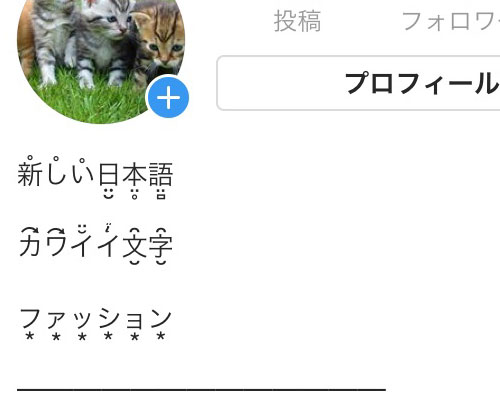
インスタのフォントで日本語をオシャレにする方法!プロフィールの日本語を変えてみよう
インスタのプロフィールには自己紹介を書く場所があって個性的なプロフィールにしている方もいますよね。
ちょっとした工夫でオシャレなプロフィールを作る事もできます。
例えば、英語(アルファベット)の場合は太字や斜体などのフォントを変える事もできます。
インスタのフォントで日本語をオシャレにする方法!プロフィールの日本語を変えてみよう
フォントが変わると印象もかなり変わりますよね。
こういうフォントで日本語の変更もできるのか気になる方も多いのではないでしょうか。
そこでこのページでは日本語のフォントについて調査してみました。
インスタのフォントで日本語をオシャレにする方法
インスタのフォントで日本語をオシャレにする方法!プロフィールの日本語を変えてみよう
まず先に結論からお伝えすると、日本語のフォント自体を変更する事はできませんでした。
しかし、日本語のフォントと記号などを加工したり組み合わせる事で日本語自体の見た目を変える事ができます。
日本語の見た目を変える方法としては以下の3つがあります。
• へた字を使う
• ギャル文字を使う
• 日本語で特殊文字を作る
それぞれの方法について以下で詳しく解説します。
へた字を使う
へた字と呼ばれる文字を使えば少し手書きっぽい日本語を使う事ができます。
例えば以下のような文字です。
कƖ ı੭ੇʑ̸̀Ⴛ̅̀
ᓓ̸₹ㄑ⇂ȷ̶ ૅੁ
ㄜιནㄝƺ
このような文字をへた字と言われています。
通常の文字よりも崩した文字で、へたな文字という感じですね。
へた字はスタイリッシュな感じではありませんが、ちょっと印象に残したいような言葉をあえてへた字にしておくと良いかもしれません。
ギャル文字を使う
ギャル文字とはガラケー時代のギャルと呼ばれる女子高生がよく利用していた文字です。
記号を組み合わせて日本語のひらがなを表現しています。
例えば、以下のような文字がギャル文字と呼ばれてます。
ぁしヽぅぇょゝ
ヵゝ(≠<しナ⊇
±U£世ξ
ギャル文字で長い文章を書かれるとパッと見は読めない状態になります。
しかし、ギャル文字に慣れてくるとちゃんと読めるようになるので面白いですね。
当時のギャルが愛用していた文字という事もあって、ギャル文字を使うとへた字よりも可愛い感じに仕上がります。
日本語で特殊文字を作る
上記で紹介したへた字とギャル文字は日本語の『ひらがな』を変える事ができましたが、漢字を変えたいというケースもありますよね。
そういう時に使えるのが特殊文字を作る方法です。
日本語で特殊文字を作ると以下のように漢字やカタカナなども可愛い感じで作る事ができます。
新̊し̊い̊日̤̮本̤̥語̤̻
カ⃕ワ⃕イ̆̈イꙶ文̮̑字̮̑
フ͙ァ͙ッ͙シ͙ョ͙ン͙
ひらがなだけならへた字やギャル文字が使えますが、漢字やカタカナを変えたい時には日本語の特殊文字を作るのが一番でしょう。
まとめ
インスタで日本語のフォントを変えるにはここで解説したように特殊文字を使う方法しかありません。
最近では特殊文字を使って日本語や英語をオシャレにしたり可愛く見せたりしているプロフィールも増えてきています。
専用のアプリをダウンロードしなくてもツールを使えば簡単にコピペできるので、日本語フォントを変えたい時はツールを活用してみると良いでしょう。
プロフィールを可愛くしてフォロワーがもっと多く増えるよう色々と試してみましょう。